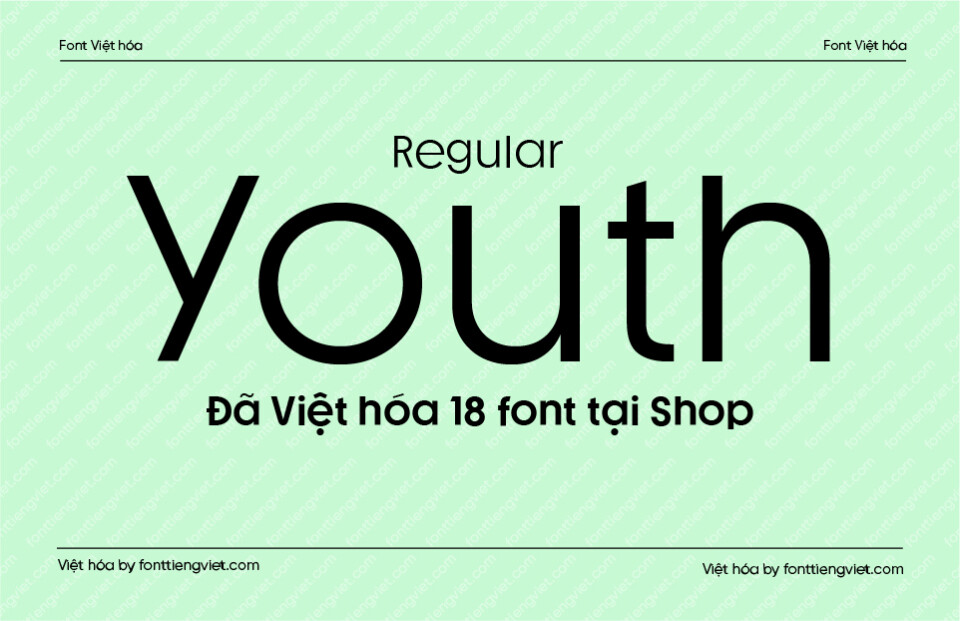
Tải Font Việt hóa 1FTV VIP Youth Regular Miễn Phí Cho Thiết Kế Học Đường Giới thiệu về Font Việt hóa 1FTV VIP Youth Regular Trong thế giới đồ họa hiện đại, việc tìm kiếm một bộ Font Miễn Phí có phong cách trẻ trung và năng động luôn là ưu tiên hàng đầu của các nhà thiết kế. Font Việt hóa 1FTV VIP Youth Regular nổi lên như một lựa chọn hoàn hảo dành cho những dự án mang hơi thở thanh xuân. Đây là bộ phông chữ được tinh chỉnh kỹ lưỡng về đường nét, đảm bảo tính thẩm mỹ cao và sự đồng nhất trong hiển thị. Với các ký tự được việt hóa chỉn chu, người dùng không còn lo lắng về lỗi font khi gõ tiếng Việt có dấu. Bộ chữ này mang lại cảm giác nhẹ nhàng nhưng không kém phần chắc chắn, giúp các thông điệp truyền tải trở nên gần gũi và dễ đi vào lòng người hơn. Đặc biệt, cấu trúc của nó rất phù hợp với môi trường giáo dục và các hoạt động của học sinh, sinh viên. Đặc điểm nổi bật của Font Việt hóa 1FTV VIP Youth Regular Thiết kế hiện đại và thanh lịch Lý do khiến Font Việt hóa 1FTV VIP Youth Regular được yêu thích chính là sự cân bằng tuyệt vời giữa các nét thanh và nét đậm. Kiểu dáng Regular giúp văn bản dễ đọc trên cả nền tảng kỹ thuật số lẫn bản in. Các góc chữ được bo tròn mềm mại, tạo cảm giác thân thiện và không quá cứng nhắc như các phông chữ kỹ thuật truyền thống. Điều này giúp cho các bản thiết kế trở nên thanh thoát và có hồn hơn. Sự tinh tế trong từng nét chữ giúp bộ font này có thể đứng độc lập làm tiêu đề hoặc kết hợp hài hòa với các kiểu chữ khác trong cùng một bố cục trang trí. Khả năng ứng dụng đa dạng trong thực tế Không chỉ dừng lại ở các ấn phẩm văn phòng, Font Việt hóa 1FTV VIP Youth Regular còn tỏa sáng trong các thiết kế poster sự kiện, bìa sách hoặc thiệp mời. Trong môi trường học đường, giáo viên có thể sử dụng font này để thiết kế bài giảng điện tử sinh động, trong khi học sinh có thể dùng để trình bày báo cáo hay tập san trường lớp. Độ tương phản vừa phải của font giúp người xem không bị mỏi mắt khi đọc các đoạn văn bản dài. Ngoài ra, phông chữ này còn rất hiệu quả khi làm phụ đề cho video hoặc xây dựng nội dung trên các trang mạng xã hội dành cho giới trẻ. Cách cài đặt và sử dụng Font Việt hóa 1FTV VIP Youth Regular tối ưu Quy trình cài đặt đơn giản Để sử dụng Font Việt hóa 1FTV VIP Youth Regular, bạn chỉ cần tải tệp định dạng .otf hoặc .ttf về máy tính. Sau đó, nhấp chuột phải vào tệp và chọn Install cho hệ điều hành Windows hoặc kéo vào Font Book đối với macOS. Sau khi cài đặt, phông chữ sẽ tự động xuất hiện trong danh sách của các phần mềm phổ biến như Photoshop, Illustrator, Canva hay thậm chí là Microsoft Word. Lưu ý nhỏ là bạn nên khởi động lại ứng dụng sau khi cài đặt để đảm bảo bộ gõ tiếng Việt hoạt động ổn định nhất với phông chữ mới này. Lưu ý khi kết hợp màu sắc và bố cục Khi trình bày với Font Việt hóa 1FTV VIP Youth Regular, bạn nên ưu tiên các gam màu tươi sáng hoặc pastel để làm nổi bật tinh thần trẻ trung của bộ font. Việc giãn cách dòng (line spacing) và khoảng cách chữ (kerning) cũng cần được chú trọng để giữ cho bố cục luôn thoáng đãng. Đừng ngần ngại sử dụng định dạng italics (nghiêng) hoặc bold (đậm) để tạo điểm nhấn cho những thông tin quan trọng trong đoạn văn. Sự linh hoạt của phông chữ này sẽ giúp bạn thỏa sức sáng tạo mà vẫn giữ được sự chuyên nghiệp cần thiết cho tác phẩm thiết kế. Kết luận về bộ phông chữ dành cho thế hệ trẻ Việc lựa chọn Font Việt hóa 1FTV VIP Youth Regular chính là một bước đi thông minh để nâng tầm chất lượng các sản phẩm truyền thông của bạn. Với sự kết hợp giữa phong cách hiện đại và khả năng hiển thị tiếng Việt xuất sắc, đây chắc chắn là công cụ không thể thiếu trong bộ sưu tập của bất kỳ ai yêu thích thiết kế. Hãy trải nghiệm ngay sự khác biệt mà bộ chữ này mang lại cho các dự án sáng tạo sắp tới của mình. Để bắt đầu, bạn có thể truy cập Font Miễn Phí, Font Việt Hóa, Font Việt hóa 1FTV VIP Youth Regular để tìm hiểu thêm và áp dụng vào thực tế một cách hiệu quả nhất ngay hôm nay.
Font Việt hóa 1FTV VIP Youth Regular